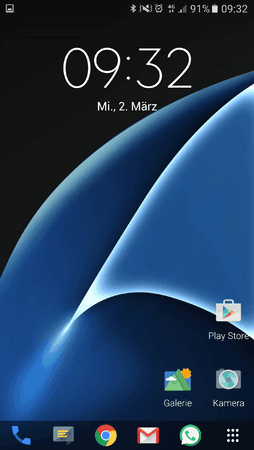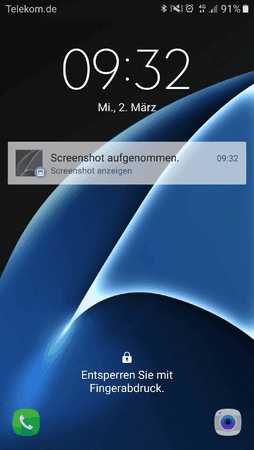
Galaxy S6 [EDGE] Sperrbildschirm Schriftart ?
weiß jemand welche Schriftart beim Galaxy S6 Sperrbildschirm bei der Uhr verwendet wird ?
SamsungSans ist es definitv nicht !
Das müsste Arial sein, wenn ich nicht irre.
ich glaube es handelt sich um Robotic-Light ...
Müsste Robotic-Light sein.
Achso, du meinst nur die Zahlen? Dachte du meinst die Schrift...
Also Robotic Light ist es nicht, sieht man an der Ziffer "3" ... jemand noch eine Idee ??
btw: es geht um die Font der Uhr ... Ich will ein Zooper Widget auf meinem Startbildschirm erstellen, das die Uhr in gleicher schriftart, größe , etc zeigt, ...
[doublepost=1456905836,1456903580][/doublepost]Was haltet ihr von SamsungNeoNum-3L ??? oder SamsungNeoNum-3T ?? (siehe anhang)
Als Theme habe ich das default TouchWiz Theme von 6.0.1 XEF. Die Uhr auf dem Startbildschirm habe ich mit Zooper selbst kreiert, sodass sie zum Stock Sperrbildschirm passt, ...